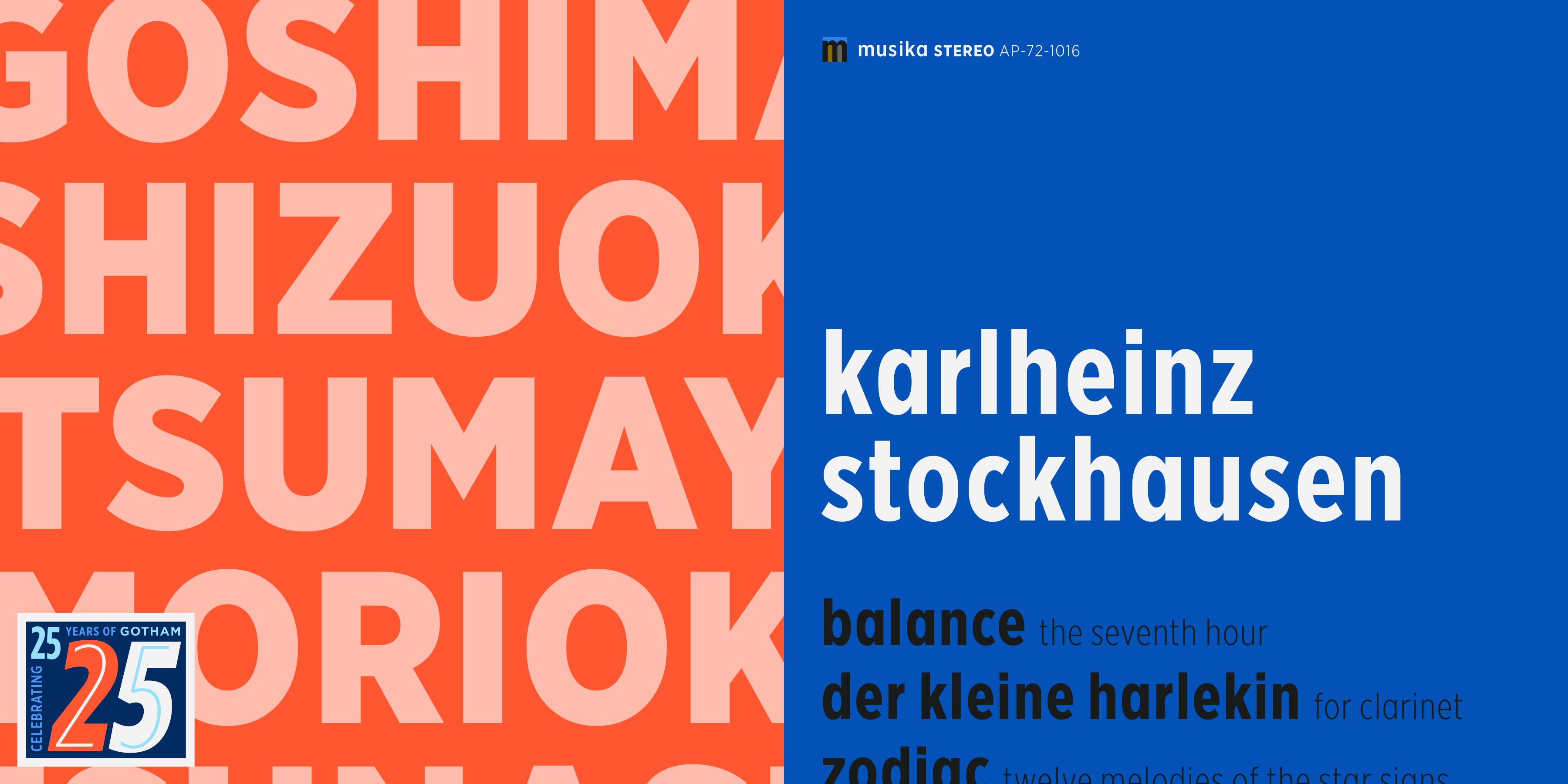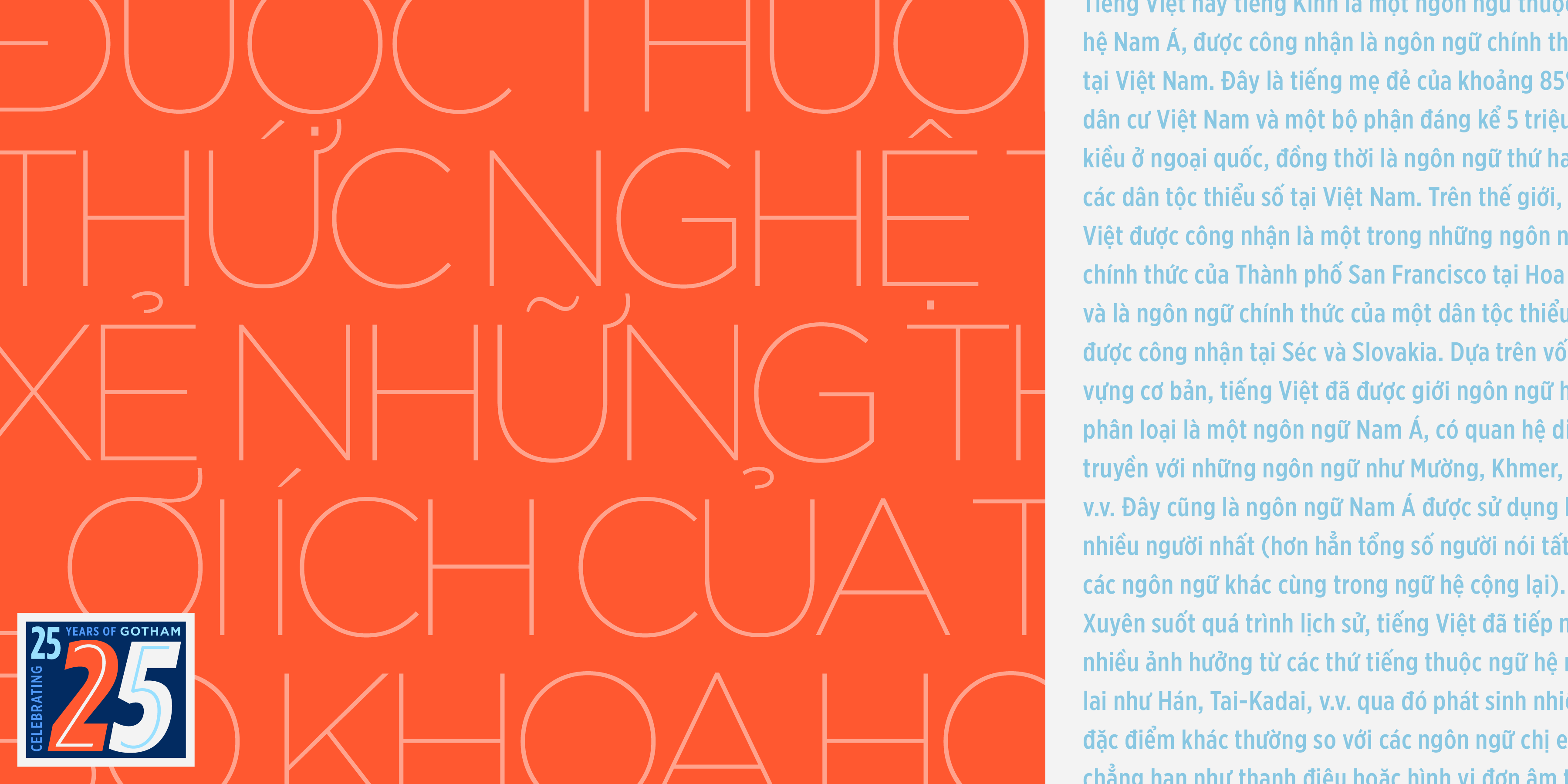
Monotype(蒙纳字库)今日正式发布 Gotham® Variable。作为经典字体 Gotham 的重磅升级之作,Gotham Variable 可在单个文件内实现字重与字宽的无级调节,现已上线 Monotype Fonts™ 与 Monotype Connect™ 平台。
作为全球极具辨识度、广泛应用的字体之一,Gotham 二十五年来深度塑造着全球视觉传播,从品牌形象、广告创意,到竞选宣传与文娱内容,应用场景无处不在。这款字体由 Jonathan Hoefler 与 Tobias Frere-Jones 设计、Hoefler & Co. 发行,2001 年 1 月首次亮相于《GQ》杂志封面。如今 Gotham Variable 续写传奇,为设计创作赋予前所未有的灵活掌控力与场景适配性。
Gotham Variable 支持字重与字宽无级调节,设计师无需切换字体、也无需牺牲视觉一致性,即可精准调整字体气质与表达效果。可变字体将多款静态字库整合为单一精简文件,显著提升运行性能、缩短加载时间,并简化跨平台部署流程,在无缝适配各类屏幕、系统与使用场景的同时,完整保留 Gotham 标志性的清晰利落与沉稳气质。
“过去 25 年间,从竞选、户外广告到全球众多标志性品牌视觉,Gotham 凭借出众品质赢得了业界高度信赖。在打造 Gotham Variable 的过程中,我们始终致力于探索这款字体的全新可能,同时坚守其不可替代的经典内核。”Monotype 执行创意总监、Gotham Variable 主创设计师 Sara Soskolne 表示。“Gotham Variable 包含诸多前所未有的全新字体样式,让这些新形态浑然天成、与经典气质融为一体,是整个项目中最具挑战,也最为核心的工作。”
在技术升级之外,Gotham Variable 进一步拓展语言支持范围,新增越南语,这也是拉丁字体体系中最后覆盖的主流语种之一。它可精准呈现复杂变音符号、叠音符与声调标记,助力品牌在全球更多地区实现清晰、地道的文字表达。
Gotham Variable 新增越南语支持Monotype 资深字体设计师 Jordan Bell 表示:“为成熟字体家族新增语种支持并非易事。确保新增字符的比例与风格严格契合 Gotham 原生气质至关重要,尤其是字符“钩”与“角”的细节,必须精准还原 Gotham 独有的表现力。”
Gotham Variable 核心特性包括:
- 单个字体文件实现字重与字宽无级调节
- 扩展文种支持,包含越南语,并优化西里尔语与保加利亚语显示
- 更丰富的字重与全新 Compact 字宽
- 提升性能、加快加载速度、简化跨平台实施
- 无缝适配数字与各类实体设计环境
在打造流畅可变体验的同时,Gotham Variable 新增 54 款静态字体,大幅拓展了字体家族的设计空间。
Gotham 曾塑造无数全球标志性视觉形象,被 Netflix、可口可乐等品牌、美国邮政署等机构,以及《Saturday Night Live》等文化平台广泛采用,还曾用于构建奥巴马总统竞选的视觉体系。
如今,Gotham 已从一套静态字体家族升级为响应式设计系统,在适配现代设计需求的同时,保留设计师长期信赖的经典气质。